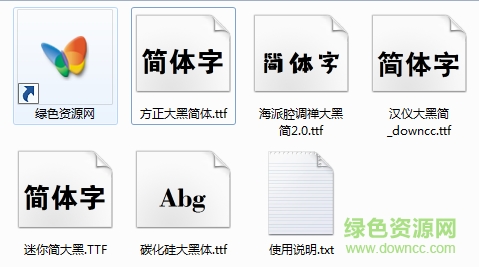
時尚大黑體打包
時尚大黑簡體是一款大方得體的時尚字體,字形更大氣顏色更深沉,很容易吸引觀眾和讀者的目光,需要的設(shè)計師們倆綠色資源網(wǎng)免費下載吧!
時尚大黑簡體字體介紹
漢字的黑體是在現(xiàn)代印刷術(shù)傳入東方后依據(jù)西文無襯線體中的黑體所創(chuàng)造的。由于漢字筆劃多,小字黑體清晰度較差,所以一開始主要用于文章標題。但隨著制字技術(shù)的精進,已有許多適用于正文的黑體字型。
時尚大黑簡體特色
黑體與白體相反,沒有襯線裝飾,筆劃粗壯有力,撇捺等筆畫不尖,使人易於閱讀。黑體是在現(xiàn)代印刷術(shù)傳入東方後依據(jù)西文無襯線體所創(chuàng)造的。所以黑體這個詞的范疇和無襯線字體是類似的。而宋體就可以被稱作襯線字體。